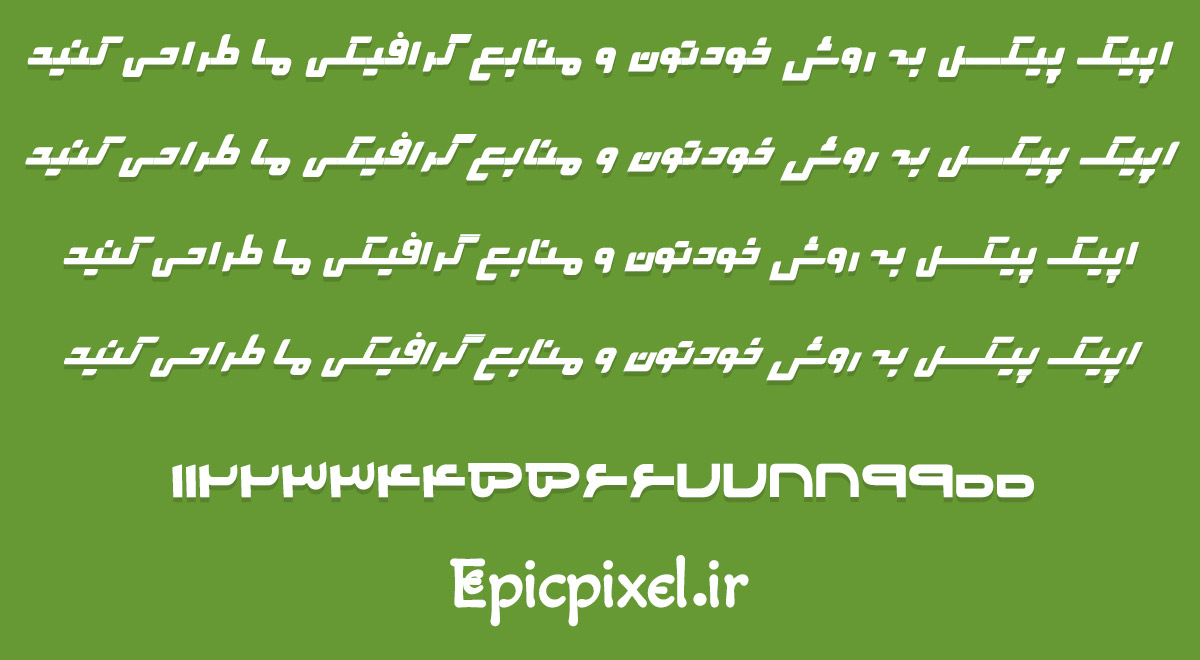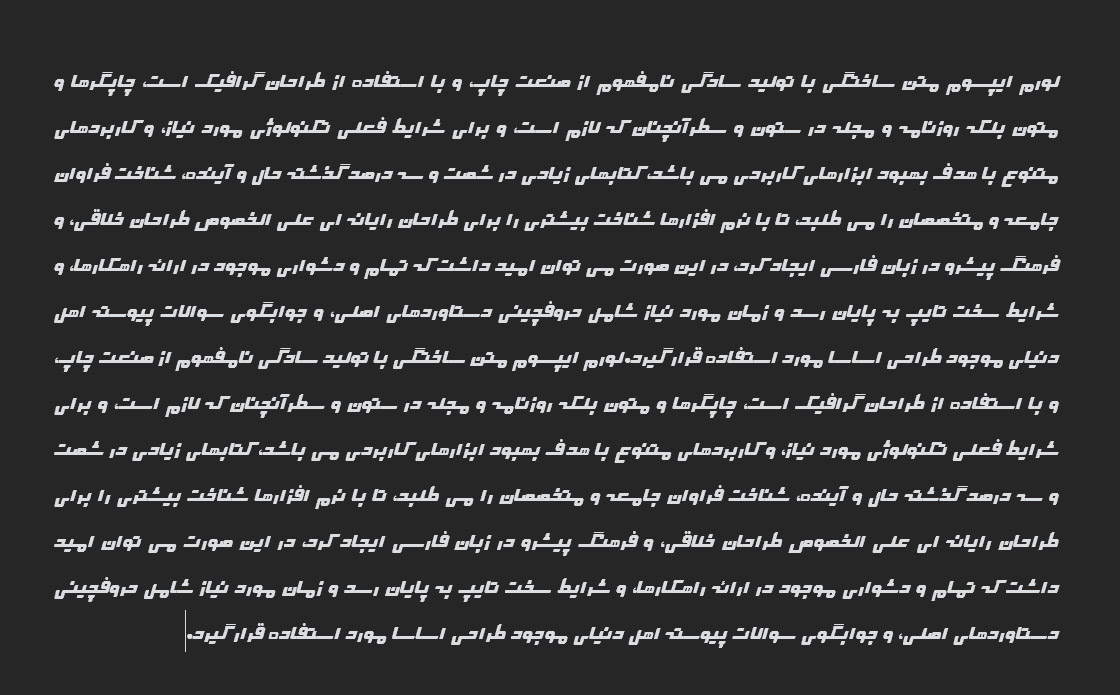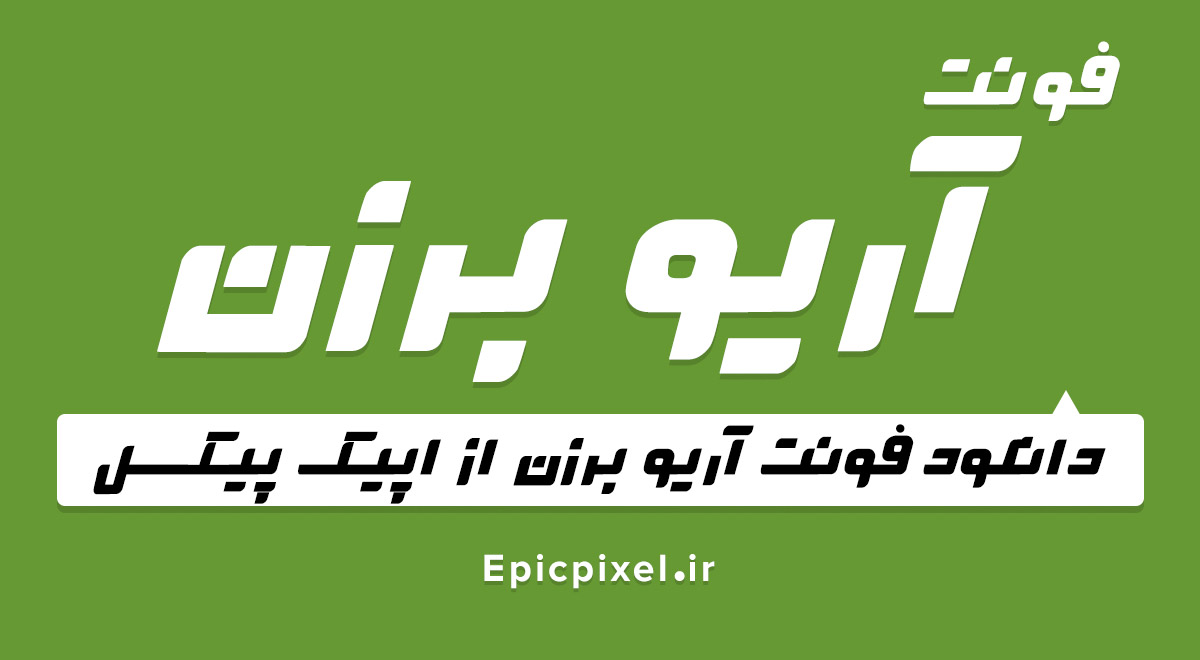
فونت آریو برزن فارسی
فونت آریو برزن تجلی شکوه و قدرت در دنیای تایپوگرافی فارسی
آشنایی با فونت آریو برزن
فونت آریو برزن، یک فونت فارسی با سبک سنگین و پویا، به طور خاص برای طراحان گرافیک و علاقهمندان به دنیای تایپوگرافی طراحی شده است. این فونت، با الهام از نام و شخصیت سردار بزرگ هخامنشی، آریوبرزن، به دنبال خلق حس قدرت، صلابت و عظمت در دنیای طراحی است.
ویژگیهای فونت آریو برزن
فونت آریو برزن، با ساختاری منظم و هندسی، در عین حال دارای جزئیات و تزئینات چشمنواز است. این فونت، با فرمتهای OTF و TTF ارائه شده و قابلیت استفاده در تمامی نرمافزارهای گرافیکی و تایپ را دارد.
کاربردهای فونت آریو برزن
فونت آریو برزن، به دلیل ویژگیهای منحصر به فرد خود، برای طیف وسیعی از کاربردها مناسب است. از جمله این کاربردها میتوان به موارد زیر اشاره کرد:
طراحی لوگوها و هویت بصری برندها
طراحی پوسترها، بنرها و تبلیغات
طراحی صفحات وب و اپلیکیشنها
طراحی انواع نوشتهها و محتوای فارسی
طراحی فونت آریو برزن
فونت آریو برزن، توسط تیم متخصص دیاکوگرافیک طراحی شده است. در طراحی این فونت، تلاش شده است تا ضمن حفظ اصول زیباییشناسی و تایپوگرافی، حس قدرت و شکوه را در قلمها القا کند.
الهامبخشی از شخصیت آریوبرزن
نام فونت آریو برزن، انتخابی هوشمندانه و خلاقانه بوده است. آریوبرزن، سردار بزرگ هخامنشی، به دلیل شجاعت، دلاوری و مقاومت در برابر ارتش عظیم اسکندر مقدونی، به عنوان نمادی از قدرت و ایستادگی در تاریخ ایران شناخته میشود.
تأثیر شخصیت آریوبرزن بر طراحی فونت
شخصیت آریوبرزن، به عنوان الهامبخش اصلی طراحی فونت، در ویژگیهای این فونت نیز منعکس شده است. ساختار قوی و مستحکم قلمها، خطوط ضخیم و در عین حال ظریف، و تقارن هندسی قلمها، همه از ویژگیهایی هستند که در شخصیت آریوبرزن نیز دیده میشود.
جایگاه فونت آریو برزن در دنیای تایپوگرافی فارسی
فونت آریو برزن، با توجه به ویژگیهای منحصر به فرد خود، در مدت کوتاهی پس از انتشار، توانسته است جایگاه خود را در دنیای تایپوگرافی فارسی تثبیت کند. این فونت، مورد استقبال طراحان گرافیک و علاقهمندان به دنیای تایپوگرافی قرار گرفته است و به عنوان یک ابزار قدرتمند برای خلق آثار خلاقانه و تأثیرگذار مورد استفاده قرار میگیرد.
فونت آریو برزن، یک انتخاب ایدهآل برای طراحان گرافیک
فونت آریو برزن، با تلفیق قدرت، زیبایی و ظرافت، یک انتخاب ایدهآل برای طراحان گرافیک است. این فونت، با پتانسیل بالای خود، میتواند در طیف وسیعی از پروژههای طراحی مورد استفاده قرار گیرد و به خلق آثار خلاقانه و ماندگار کمک کند.